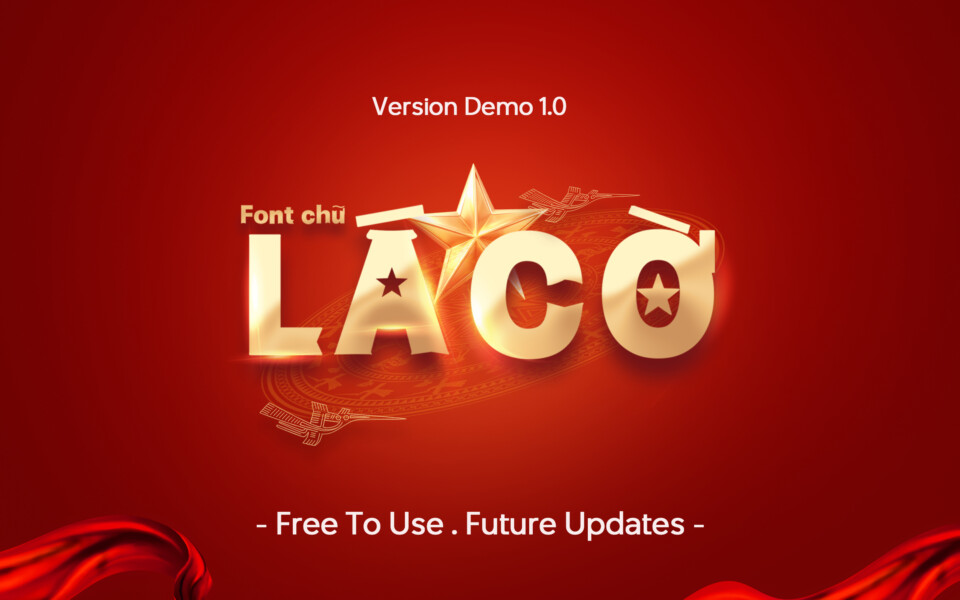
Font Tiếng Việt – Lá Cờ – Bộ Font Chữ Ý Nghĩa Cho Giáo DụcGiới thiệu về Font Tiếng Việt – Lá CờTrong các hoạt động thiết kế học đường, việc lựa chọn một bộ Font Miễn Phí phù hợp đóng vai trò vô cùng quan trọng. Bộ Font Tiếng Việt – Lá Cờ ra đời như một giải pháp thiết kế lý tưởng, mang đậm tinh thần tự hào dân tộc. Được lấy cảm hứng từ hình ảnh lá cờ Tổ quốc tung bay, bộ phông chữ này sở hữu các đường nét thanh thoát, vừa trang nghiêm lại vừa gần gũi với học sinh. Đây là công cụ đắc lực giúp các thầy cô và các em học sinh dễ dàng sáng tạo nội dung học tập một cách trực quan và sinh động nhất.Ứng dụng thực tế của bộ font trong nhà trườngThiết kế bài giảng và slide thuyết trìnhBộ Font Tiếng Việt – Lá Cờ cực kỳ phù hợp để ứng dụng vào các bài giảng điện tử, đặc biệt là các môn học như Lịch sử, Địa lý và Giáo dục công dân. Nhờ định dạng việt hóa hoàn chỉnh, phông chữ này không bị lỗi dấu tiếng Việt khi gõ trên các phần mềm thông dụng như PowerPoint hay Word. Điểm độc đáo của bộ chữ giúp học sinh dễ dàng tập trung, tiếp thu bài học nhanh chóng và hứng thú hơn với những kiến thức lịch sử nước nhà.Làm báo tường và trang trí lớp họcMỗi dịp lễ lớn như Ngày Nhà giáo Việt Nam 20/11 hay Ngày thành lập Đoàn 26/3, việc làm báo tường sẽ trở nên nổi bật hơn bao giờ hết nhờ tiêu đề sử dụng Font Tiếng Việt – Lá Cờ. Thầy cô và học sinh có thể dùng bộ chữ này để in ấn áp phích, làm bảng tin lớp học hoặc thiết kế các trò chơi ngoại khóa vui nhộn, tạo không gian học tập đầy sáng tạo.Kết luận và hướng dẫn tải font chữCó thể thấy, bộ phông chữ này mang lại giá trị thẩm mỹ cao và khơi gợi lòng yêu nước cho thế hệ trẻ. Nhà trường và học sinh có thể tìm kiếm Font Miễn Phí, Font Việt Hóa, Font Tiếng Việt – Lá Cờ để tải về sử dụng ngay cho các dự án sáng tạo sắp tới.
Font Tiếng Việt – Lá Cờ